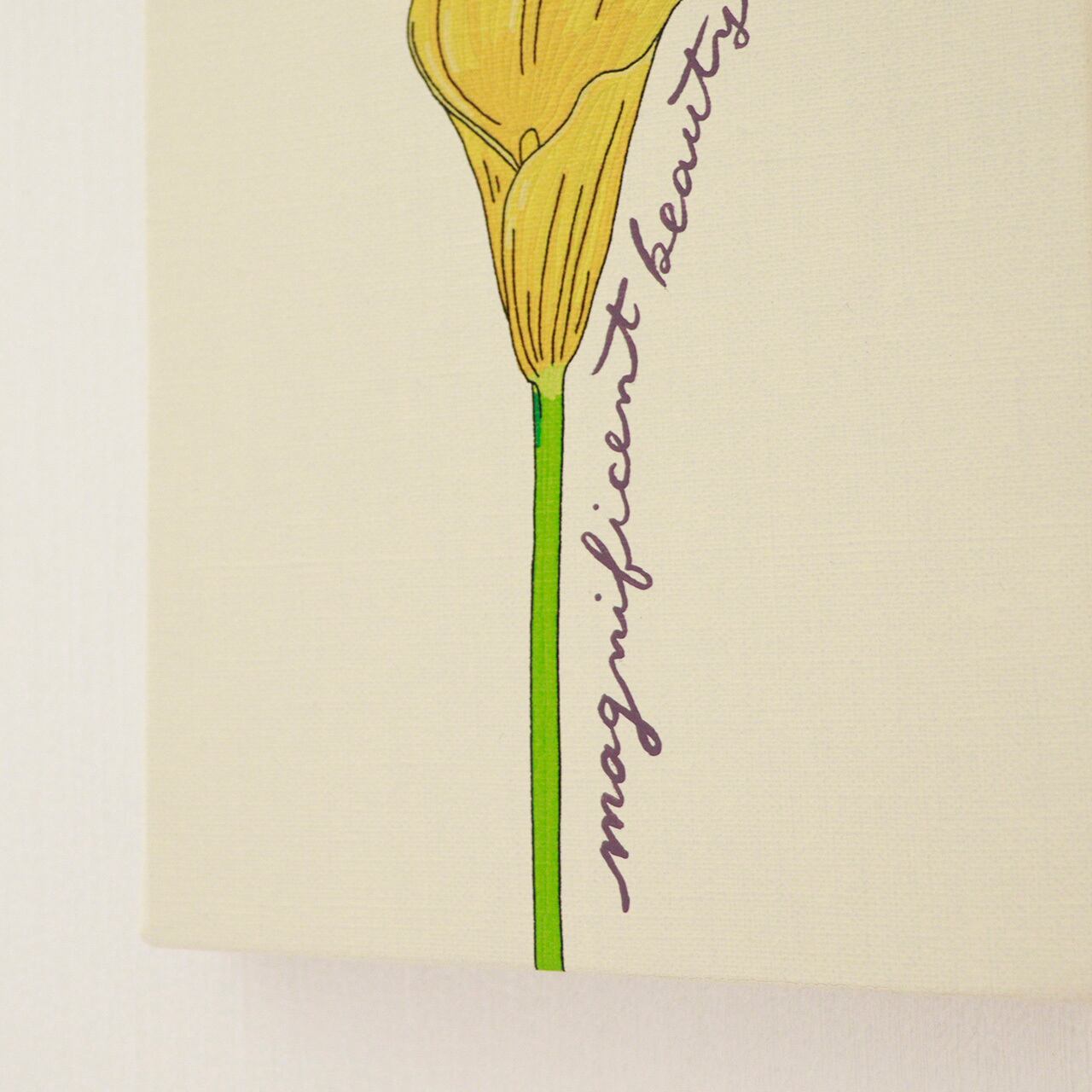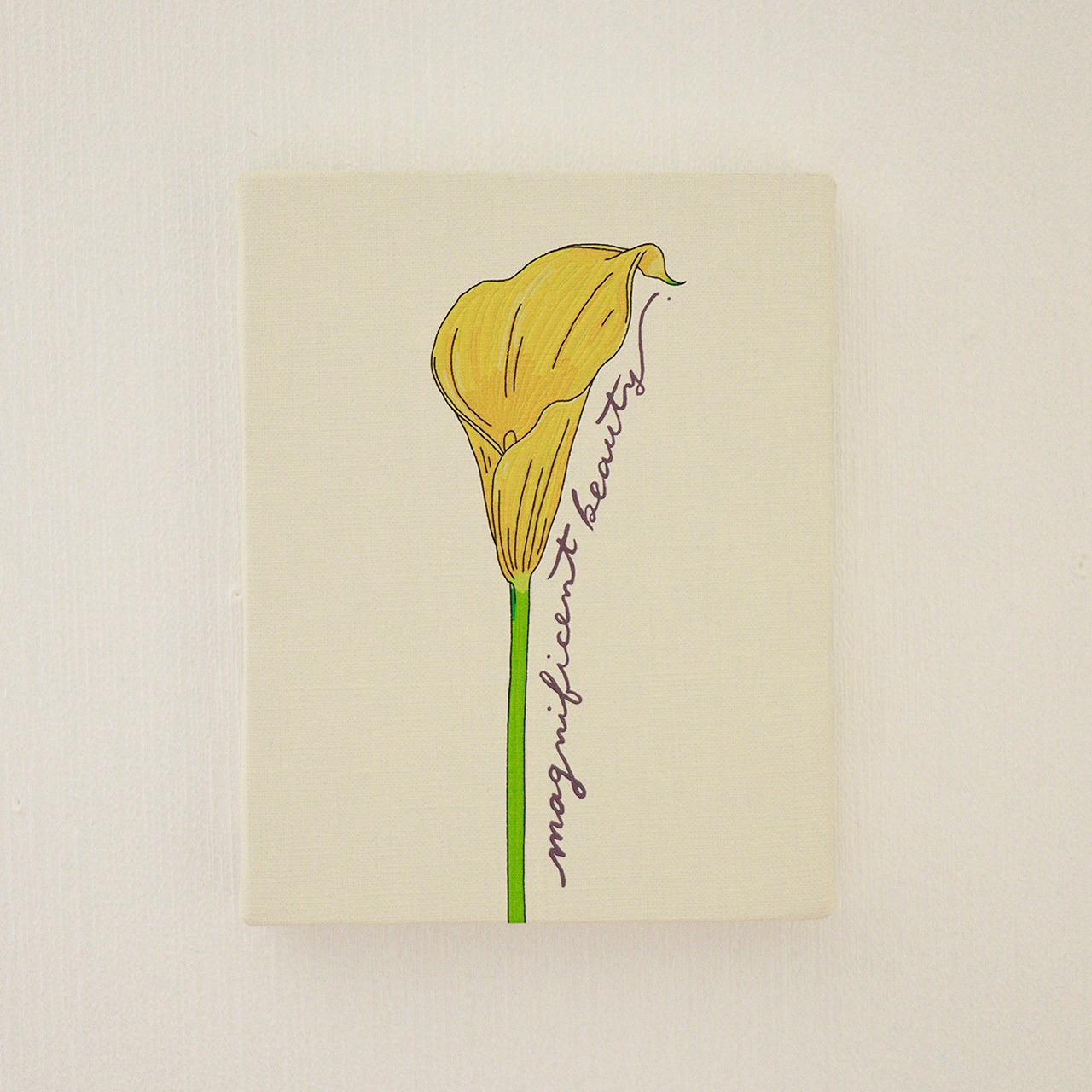
a flower 002 / magnificent beauty
a flower 002
一輪の花を摘むように選んでほしい
a flower シリーズ
私の大好きな花のひとつ、カラー。
凛とした佇まいがとても素敵なので、
花に沿わせるように花言葉をそのまま描きました。
花束を飾るように、お部屋の壁に飾ってくださいね◎
○イラスト:印刷 文字:水性塗料使用